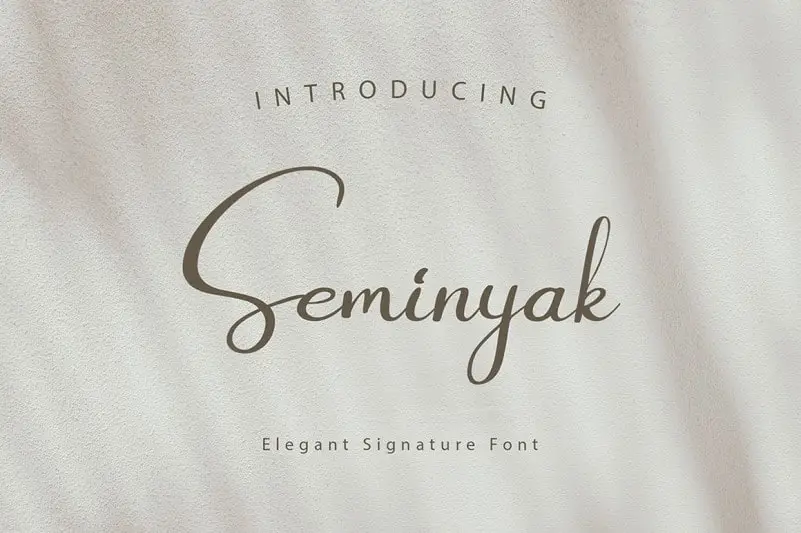
A Seminyak Script Font é uma maravilhosa tipografia script que brilha especialmente para headlines e parágrafos em todas as escalas. Suave e agradável ao olhar, ela se adapta perfeitamente tanto para o formato web quanto para o impresso, ou até mesmo movimentos visuais. Este font é uma escolha excepcional para aqueles que buscam um equilíbrio único entre sutileza e forte impacto visual. Com suas variações de texto tanto em tamanho máximo quanto mínimo, a Seminyak Script Font se destaca como uma solução versátil que pode ser utilizada em diferentes ambientes gráficos. De websites modernos até capas de revistas elegantes, este font não deixará ninguém indiferente com seu estilo único e arrojado. Ideal para quem busca incorporar um toque especial à sua criação visual, a Seminyak Script Font é uma escolha inteligente que certamente fará seu trabalho em qualquer formato ou aplicação de mídia.